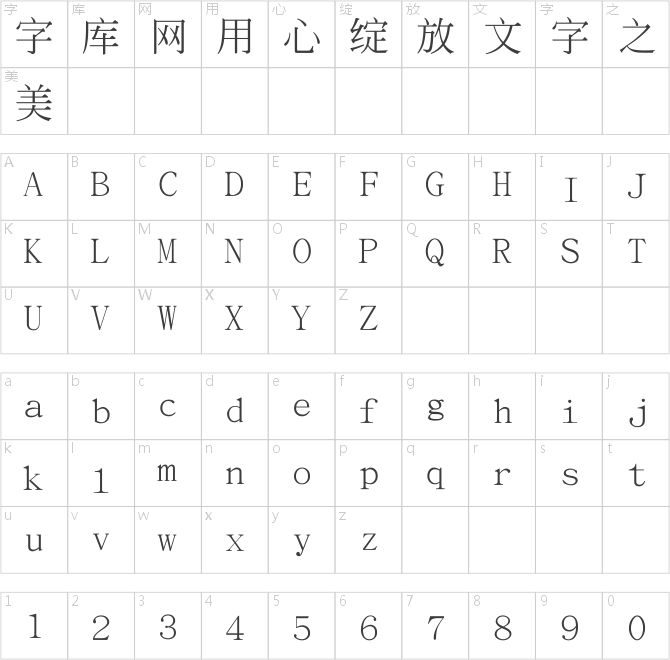
宋體
文鼎
簡體
繁體
明體
文鼎書宋的簡體和big5、gb2312繁體合并成了文鼎書宋簡繁,二次修訂時補(bǔ)了缺失的三個字符并加入了7個二簡字,三次修訂時修復(fù)了postscript名稱重名的情況。該字體向上兼容新版win10。
更新Power TrueType Version 5.0版,和原Power TrueType Version 4.0或Power TrueType Version 4.5版本相比又將原Power TrueType big5的擴(kuò)展471個外字集的部分沒有映射字碼點的漢字進(jìn)行了對號入座,并修復(fù)『?』字誤映射到『抝』字位置的錯誤。